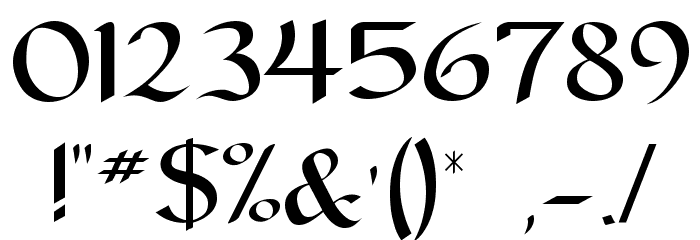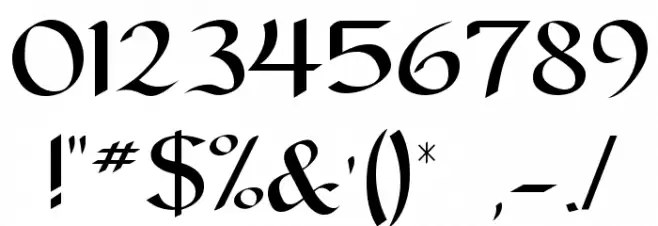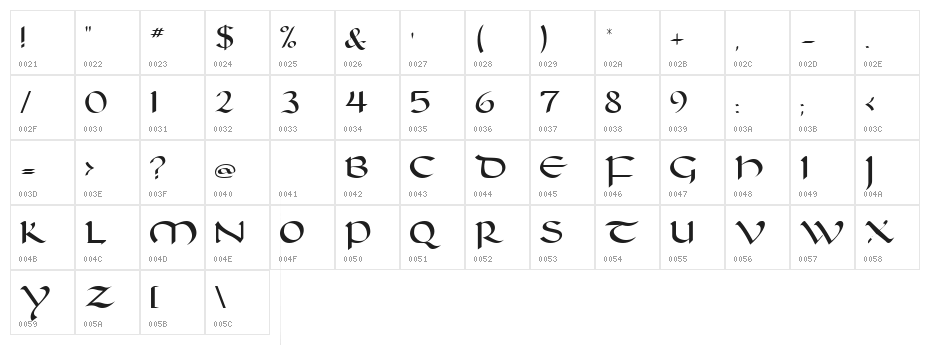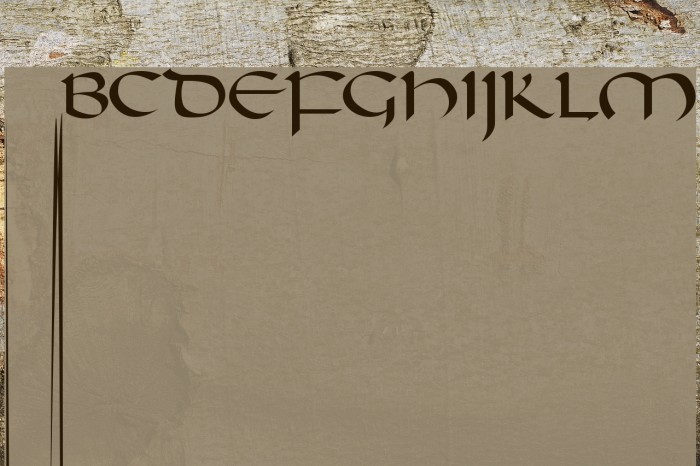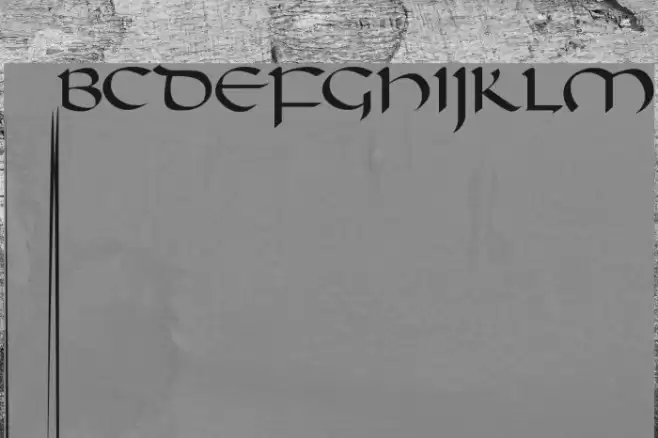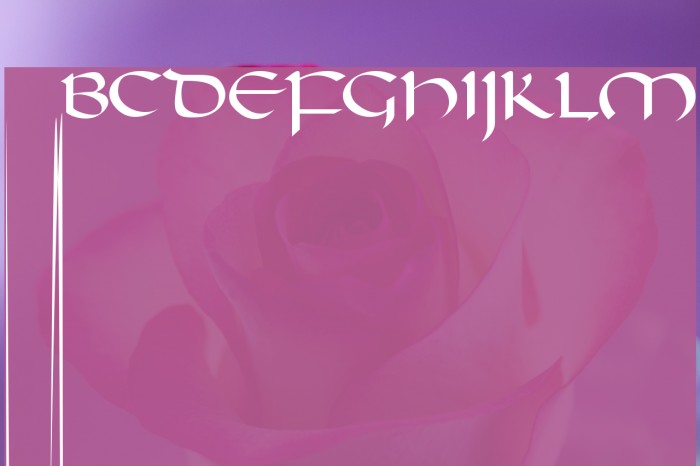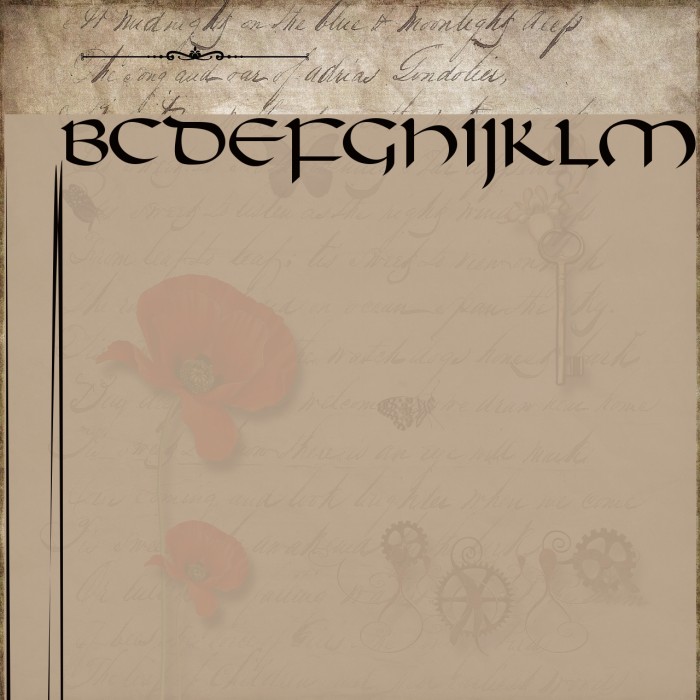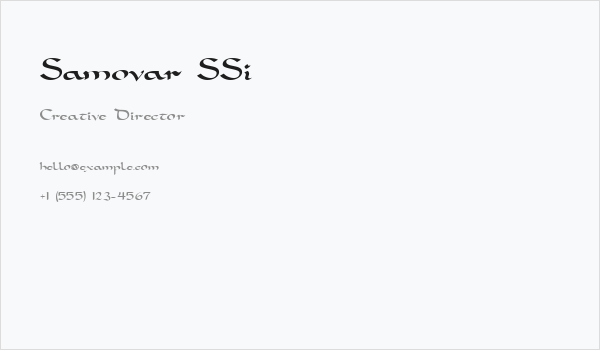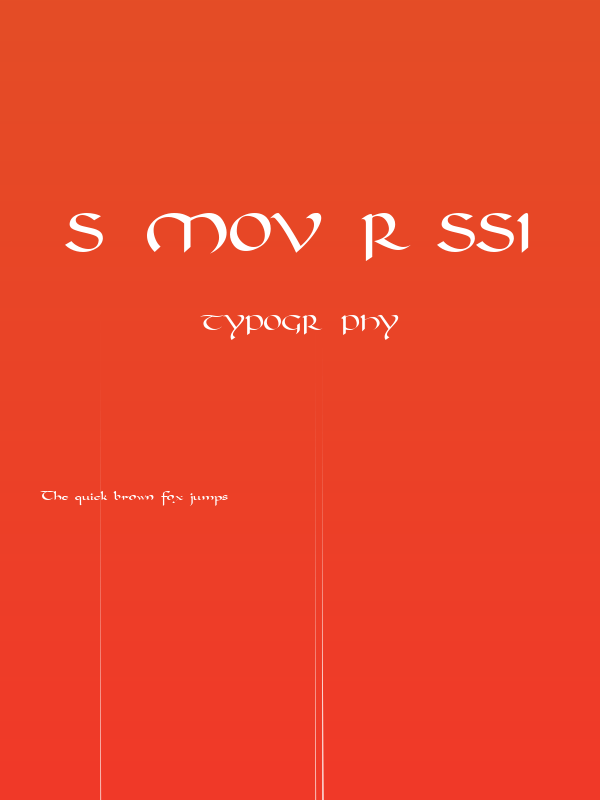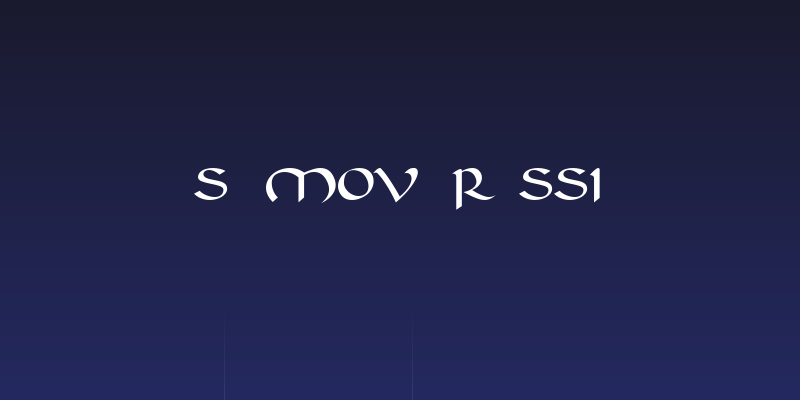
Samovar SSi Font
| Stile generale | Gothic |
| Caso d'uso | Headlines, Logos, Decorative text |
| Progetti proposti | Ideal for book covers, posters, branding, and any project requiring a medieval or gothic aesthetic. |